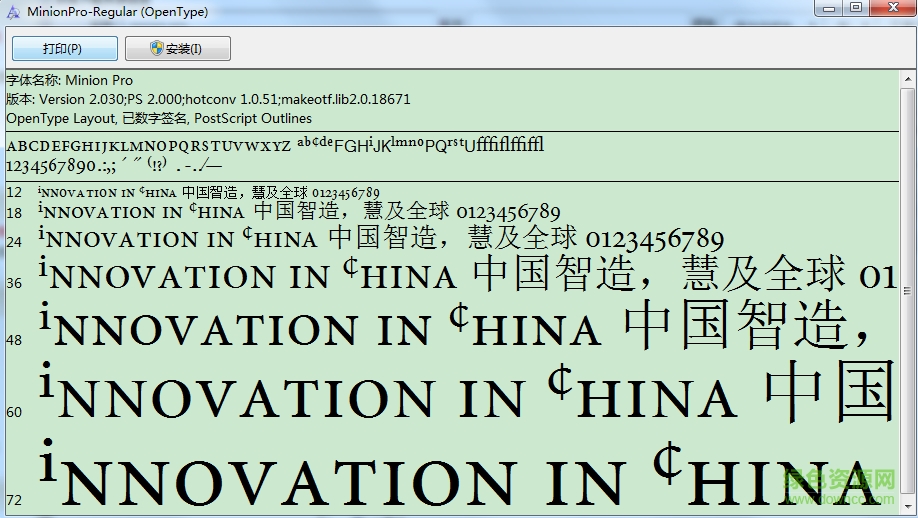
minion pro是一款常用的英文字體,這款字體線條優(yōu)雅,筆畫流暢,看起來非常出錯,喜歡這款字體的朋友歡迎來綠色資源網(wǎng)免費下載使用。
minion pro字體是一款實用性很強(qiáng)的英文字體,清晰易讀,結(jié)構(gòu)輕巧、可用于報刊、廣告、海報等設(shè)計領(lǐng)域,有需要者快來綠色資源網(wǎng)下載吧!